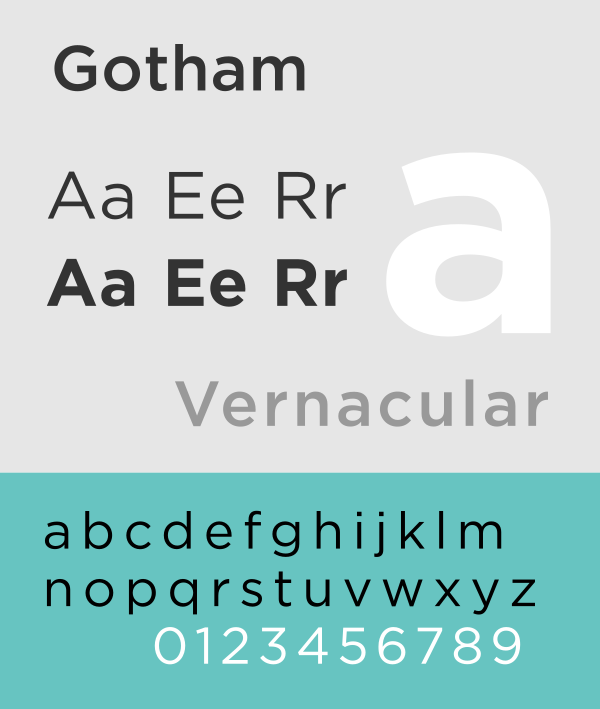
Готэм (шрифт)
Готэм — семейство геометрических гротесков, разработанное американской компанией Tobias Frere-Jones в 2000 году[1]. На создание шрифта дизайнеров вдохновили вывески на улицах городов, распространённые в середине XX века, которых особенно много в Нью-Йорке[2].
Шрифт Готэм изначально разрабатывался по заказу журнала GQ, редакторы которого хотели получить для их издания геометрический гротеск, который бы выглядел «мужским, свежим и новым»[3].
С момента своего создания шрифт Готэм достаточно широко использовался в различных компаниях. Самое значительная из них — предвыборная кампания Барака Обамы в 2008 году. Также Готэм используется в айдентике Всемирного торгового центра 1, который воздвигнут на месте разрушенных Башен Близнецов.
Готэм также использовался в титрах фильмов «Начало» Кристофера Нолана, «Луна» Данкана Джонса, «Боец» Дэвида О. Расселла и «Одинокий мужчина» Тома Форда, а также в оформлении постеров к ним. В разных своих вариациях Готэм используется в геосоциальной сети Foursquare.
| Gotham | |
| Стиль | Шрифты без засечек |
| Классификация | геометрический гротеск |
| Дата создания | 2000 |
| Дизайнер | Tobias Frere-Jones[d] |
| Словолитня | Hoefler & Co.[d] |